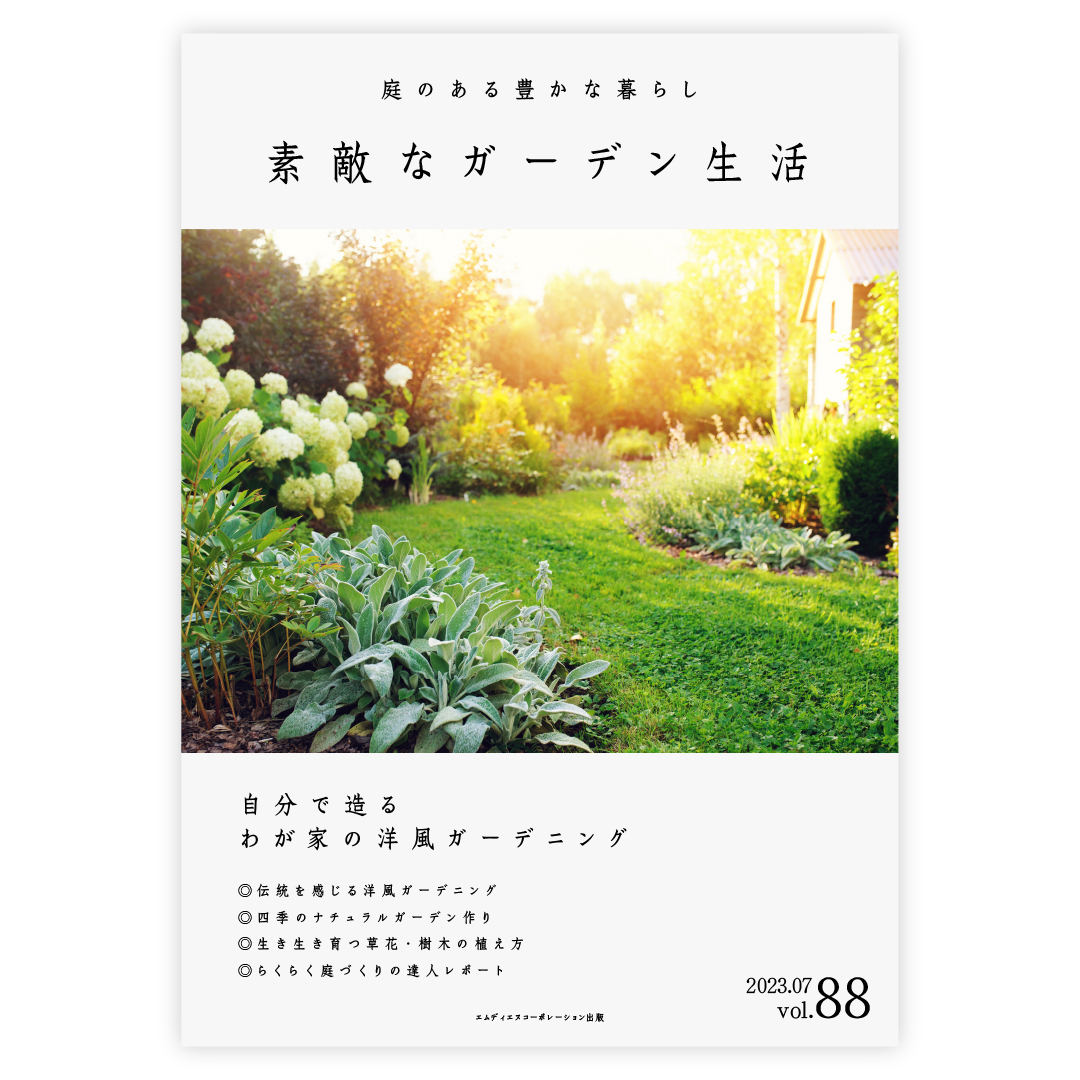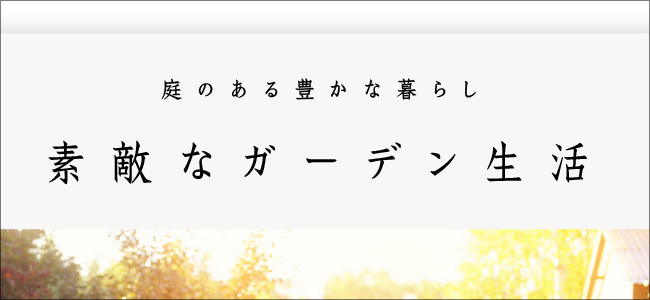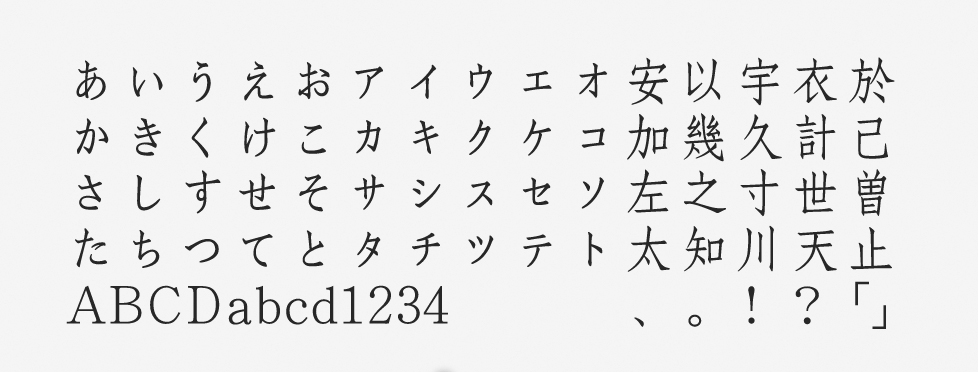
「花胡蝶」について
花胡蝶はもともとはリョービイマジクスの「伝統書体シリーズ」として発売されたフォントで、台湾で漢字、日本でかな文字が開発されました。同シリーズには花胡蝶のほかに、楷書体の花蓮華や隷書体の花牡丹が含まれます。花胡蝶は中国刊本字様、特に南宋刊本の歴史を継承したデザインで、一般的に宋朝体と呼ばれるフォントです。
「花胡蝶」の特徴
文字はやや縦長の設計で、力強い起筆や曲げとハネの鋭さなどが特徴です。ハライの先端は大きくて、鋭角にデザインされています。かな文字は宋朝体らしい処理を踏襲しつつも癖を弱め、漢字と比べてやや小さめの字面です。そのため、読みやすい本文組みを実現するためには特に効果を発揮します。
花胡蝶を用いると、軽やかで格調高いイメージに仕上がります。本文書体のほかにも、名刺や案内状などの用途でも有効です。
作例は、洋風ガーデニングの雑誌のデザインです。やや縦長のフォントである花胡蝶を使って、その魅力がさらに際立つようにアケ組みにしています。花胡蝶は漢字とかな文字の字面の大きさが異なるので、長文を組んだときにリズム感が生まれやすいのも魅力でしょう。